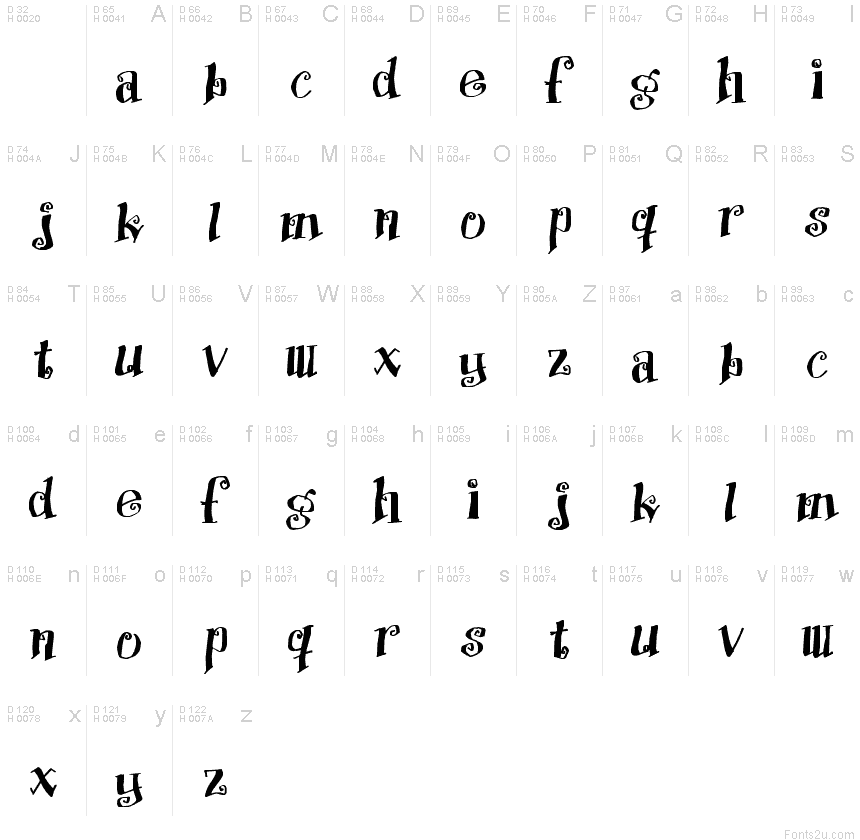
Protection od Jakoba Fischera to darmowy krój wyświetlaczowy z klimatem gotyckich baśni. Litery opierają się na surowych, ręcznie ciosanych kształtach i długich, zwężających się pociągnięciach, które przełamują gotycką powagę figlarnymi zawijasami. Wychodzą one z liter „r”, „t” oraz „e”, nadając całemu krojowi żwawy, lekko przekorny charakter.
Świetnie sprawdza się na okładkach książek fantasy, ulotkach na Halloween, szyldach karczm, plakatach tematycznych czy w napisach tytułowych, gdzie średniowieczny klimat potrzebuje więcej polotu niż patosu. Jako darmowy font pasuje również do krótkich haseł reklamowych, początków rozdziałów i inicjałów, ponieważ te kręcone linie nadają nawet kilku literom wystarczająco dużo charakteru, by ożywić stronę.
Protection